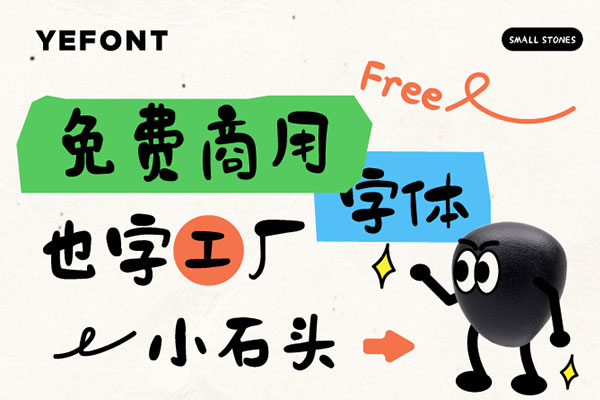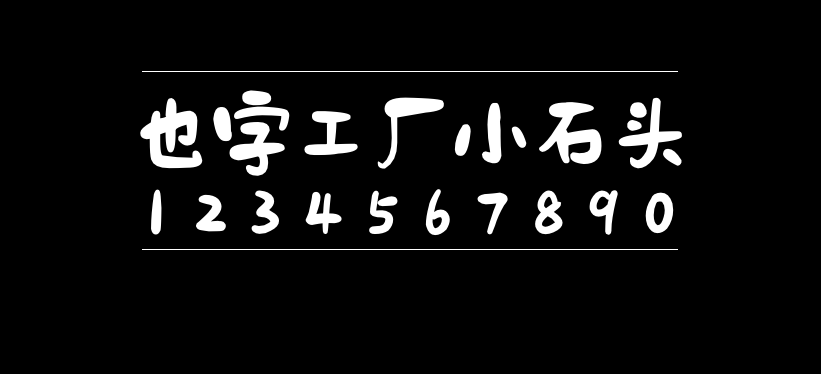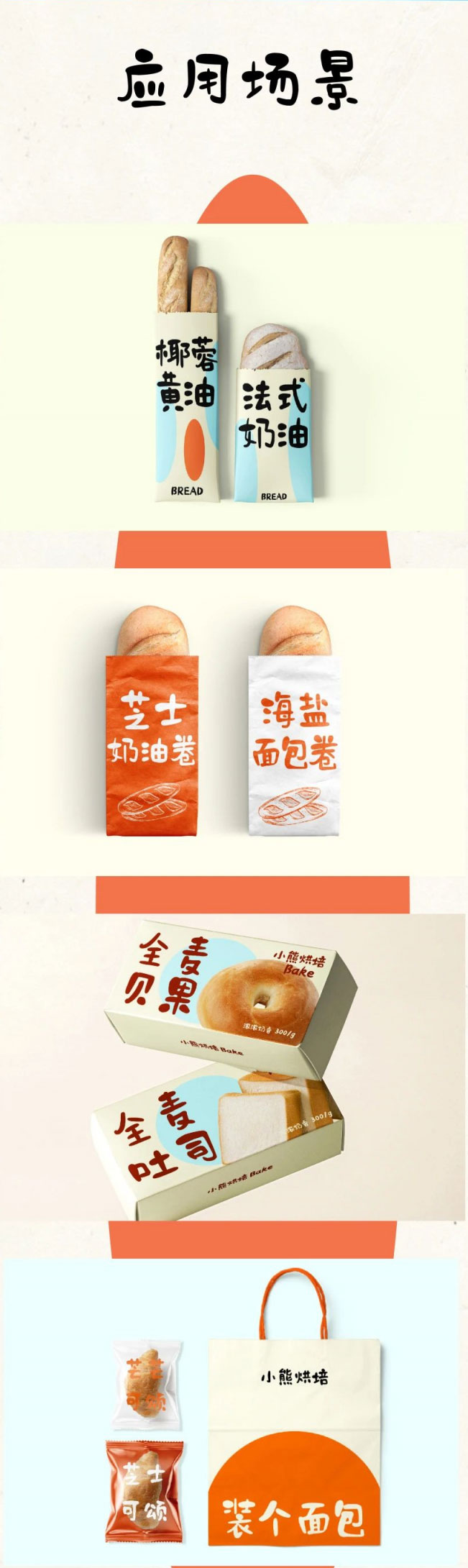
也字工厂小石头
也字工厂小石头(YEFONTXiaoShiTou)是也字工厂推出的第一款免费商用字体,该字体字形Q弹,让人感受到柔软、可爱的氛围,增添了字体的亲和力。笔画的书写方式自由、随意,展现出一种洒脱、率真的风格,使整体更具活力和个性。通过巧妙运用软笔的圆润特征,字体的笔画显得灵动活泼,给人一种温暖亲切的感觉。同时,字体的笔画粗细对比强烈,增加了视觉冲击力,让字体更加引人注目。这些特点使小石头字体成为一种充满活力和趣味的选择,适合用于各种设计场景,为作品增添独特魅力。
字体应用领域:包括但不限于创意设计领域、卡通形象设计、儿童书籍、广告宣传等。